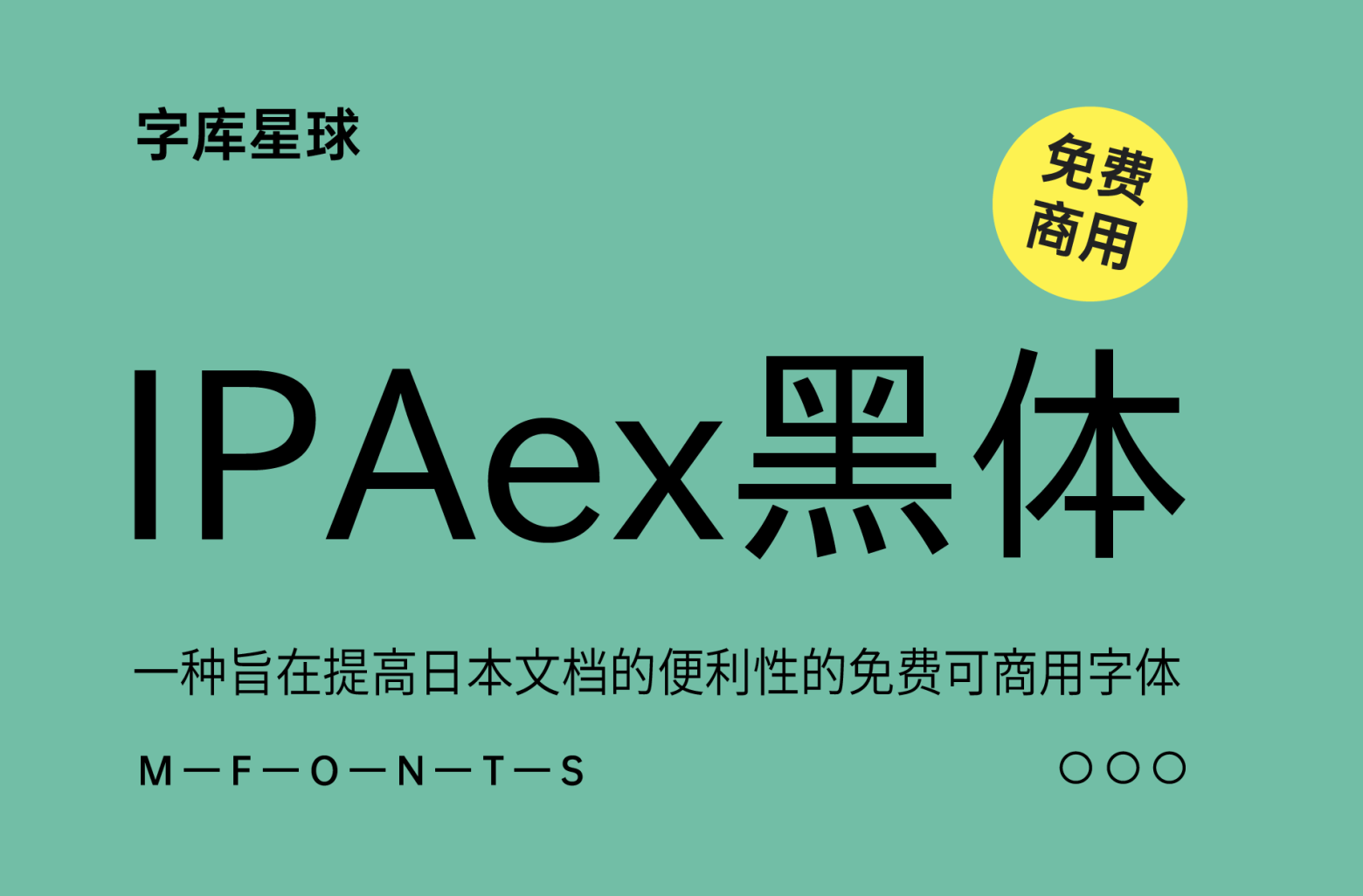
自2003年底以来,IPA一直在发布IPA拥有所有权利的“ IPA字体*”。 2010年2月,将IPAEX字体(IPAEX明朝体,IPAEX 黑体两种字体)添加到阵容中,这是日本字体的标准实现文档字体。 “ IPAEX字体”是一款旨在提高日本文档的便利性的字体,日本文字(例如Kana和Kanji)以固定宽度实现,欧洲文字是可变宽度以匹配文字宽度的可变宽度。
如果您想与过去的系统兼容,还可以使用四种类型的字体:“ IPA明朝体”和“ IPA黑体”,它们的欧洲和日本文字都具有固定宽度,以及“ IPA P 明朝体”和“ IPA P 黑体”,它们的欧洲和日本文字具有可变宽度。 “ IPAEX字体(VER.001及以后)”和“ IPA字体(Ver.003及以后)”是获得许可的“ IPA字体许可证”,这与国际实践作为开源许可证是一致的。该许可证在2009年4月1日获得OSI认证为“开源计划”(OSI)“开源定义(OSD)”。 *IPA字体是IPA的注册商标。
IPAex黑体是日系字体,所以简体缺字比较多。不过热心的国内设计师@落霞孤鹜为IPAex黑体这一高质量的日文字体补全简繁常用字,字体命名为霞鹜新晰黑。